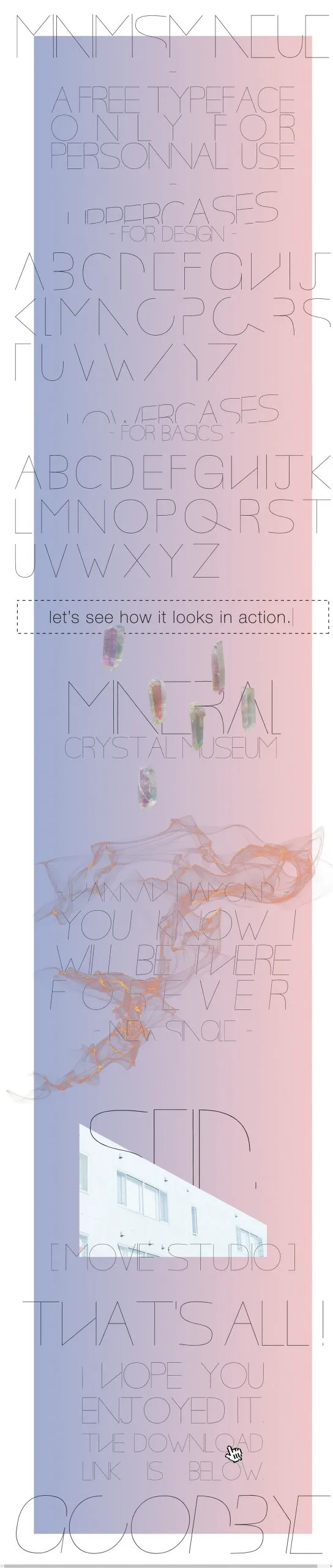
A Minimism Neue Typeface é uma escolha perfeita para designers buscam um look clean e moderno em seus projetos digitais. Ela foi criada pelo talentoso Hamilton, com linhas finas e leves que garantem um aspecto minimalista incrivelmente sofisticado. A tipografia é a sinônimo de simplicidade e clareza, ideal para textos legíveis em diversos tamanhos. Suas características curvas simples e retas sólidas criam uma aparência moderna e atemporal que se adapta perfeitamente tanto aos websites quanto ao design gráfico tradicional. Com a Minimism Neue Typeface, você pode ter um estilo elegante sem perder o foco de suas mensagens.